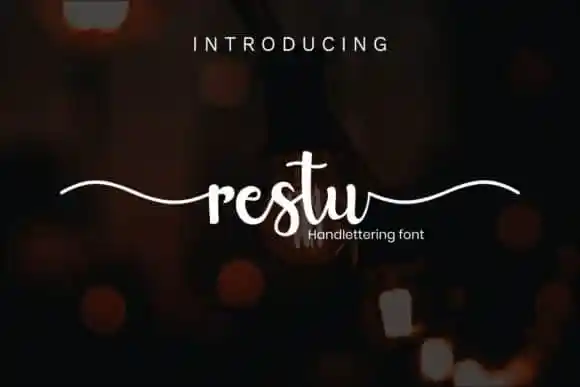
Restu Calligraphy Font – Download Grátis
A Restu Calligraphy Font é uma escolha irresistível para aqueles que buscam um toque elegante em seus projetos digitais. Desenvolvida com cuidado para incorporar elementos de elegância e autêntica escrita, esta fonte estilizada se destaca por seu design clássico e sua sensação amigável. Perfeita para aplicativos variados como cabeçalhos, logotipos, cartões de visita, citações impressas, convites (para casamentos, aniversários, uniões etc.), embalagens, currículos e até mesmo o branding em seu site ou mídia social, a Restu Calligraphy Font é um complemento perfeito para qualquer projeto que você tenha em mente. Seja você um designer ou uma empresa inovadora, ela trará um toque autêntico de elegância à sua identidade visual.